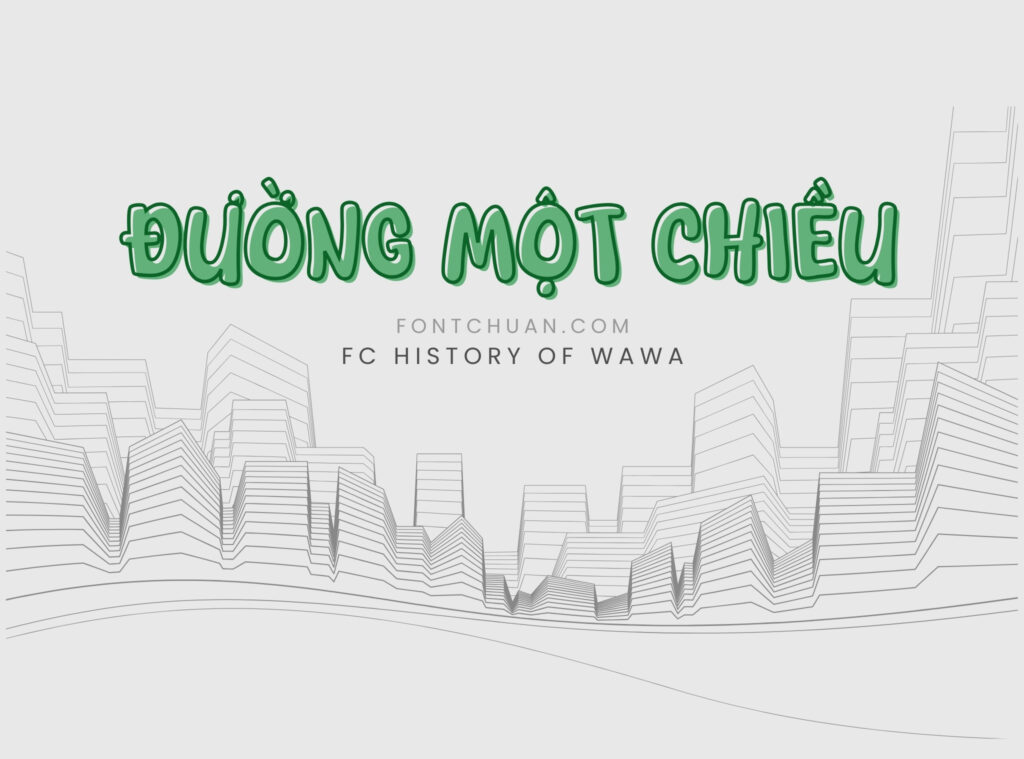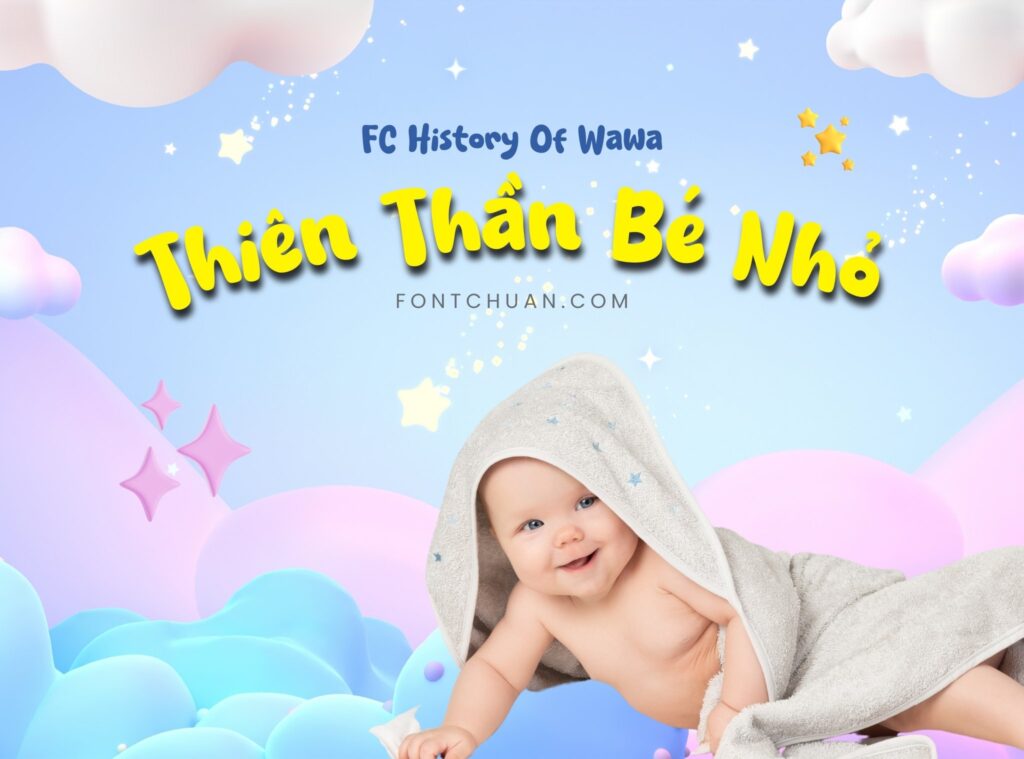
Font FC History Of Wawa Việt Hóa
Tác giả Font: Khurasan
History of Wawa là một font chữ hoạt hình vui nhộn, được thiết kế bởi Syafrizal, còn được biết đến với tên Khurasan. Font này mang phong cách đường vẽ độc đáo, với các nét chữ mềm mại và uyển chuyển, tạo nên sự thân thiện và gần gũi cho người xem. Bên cạnh các ứng dụng trên, History of Wawa cũng có thể được sử dụng như một Font Lễ hội hoặc Font chữ Halloween để tạo điểm nhấn sinh động, vui tươi cho các ấn phẩm sự kiện, poster, banner hoặc thiệp mừng đặc biệt. Nếu biết dùng đúng, nó vẫn nổi bật để tạo cảm giác chút creepy cho ấn phẩm Halloween của bạn.
History of Wawa hỗ trợ đa ngôn ngữ nhưng tiếng Việt chưa đầy đủ, vì vậy phiên bản Việt hóa FC History Of Wawa được Font Chuẩn thực hiện và chia sẻ miễn phí (khác với bản có thể có phí xu hoặc thành viên VIP), nhằm đáp ứng nhu cầu sử dụng tiếng Việt trong thiết kế.
Font FC History Of Wawa Việt Hóa
Về thiết kế, History of Wawa sở hữu các đường nét mượt mà, cấu trúc chữ cân đối và phong cách vui tươi, phù hợp cho nhiều mục đích sử dụng như thiết kế sách thiếu nhi, thương hiệu vui nhộn, áp phích và các ấn phẩm quảng cáo khác.